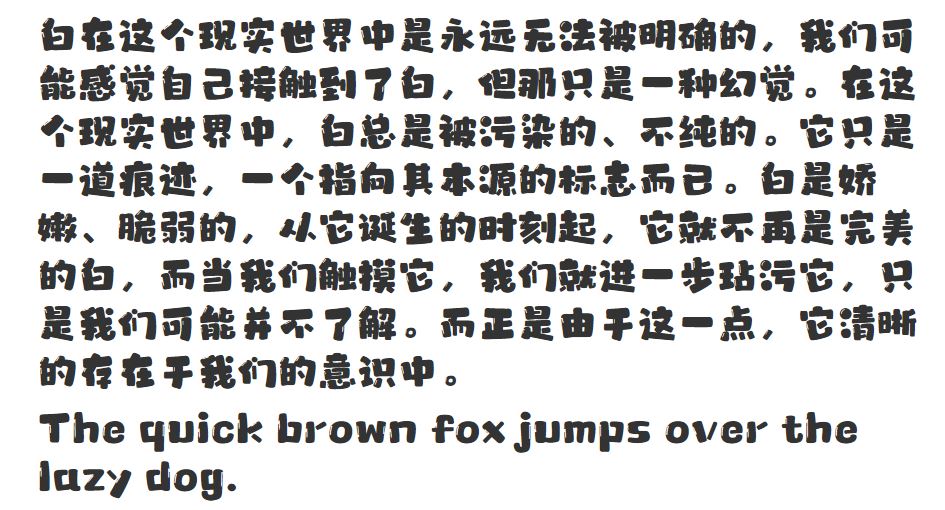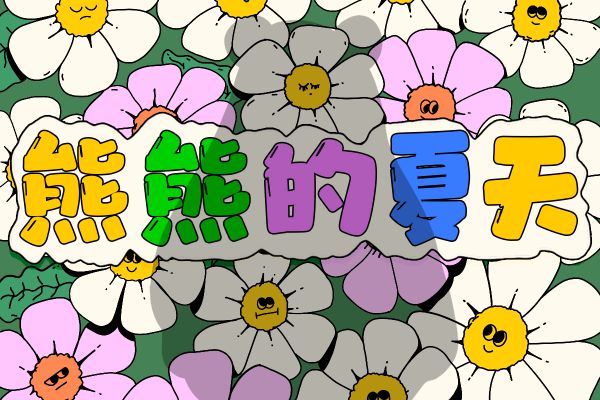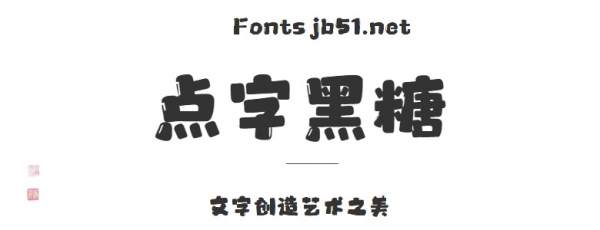
點字黑糖字形憨態(tài)可掬、跳躍俏皮,形象生動靈活。高光的效果使字體看起來更活潑,可愛。適合于文化類的宣傳設計、商業(yè)類品牌的廣告和產品包裝設計以及個性化文字排版等較多場景。
字符集 GB2312+拉丁字符
風格
溫和親切 / 有趣/卡通/創(chuàng)意字體
應用領域
標志 / 廣告 / 游戲 / 動漫 / 影視 / 包裝
字體應用示例